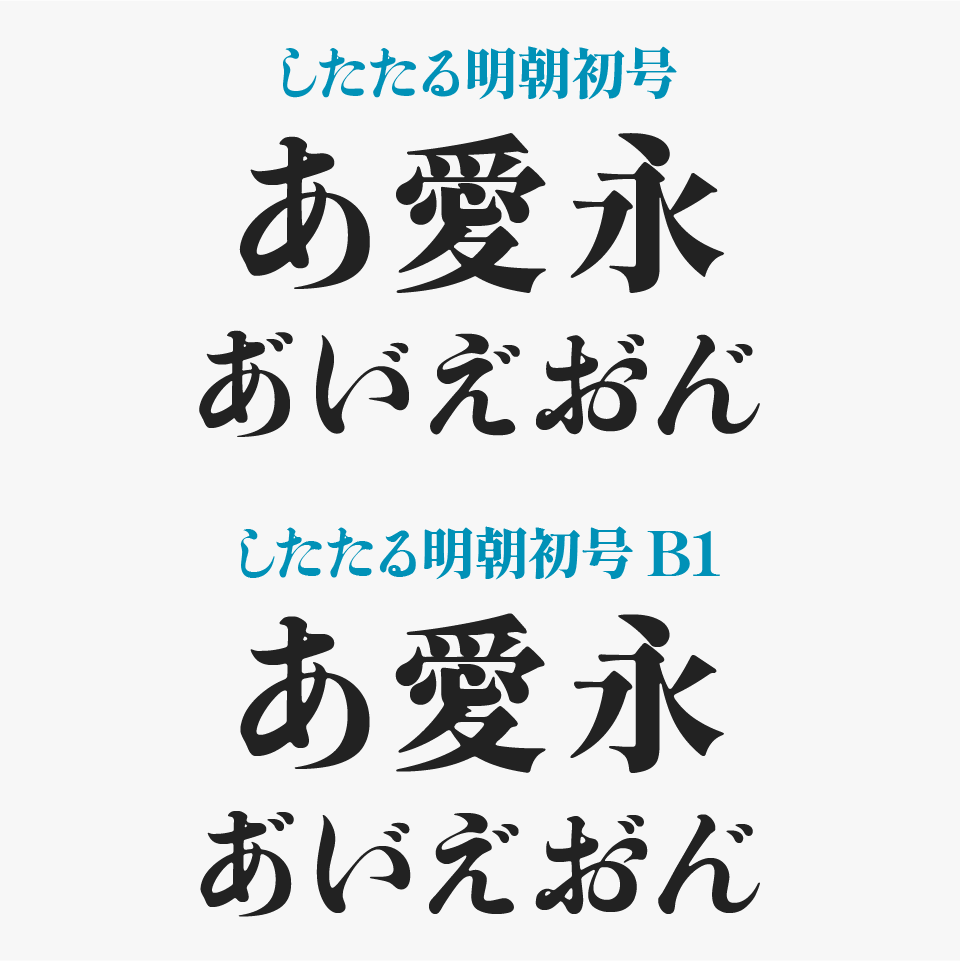
したたる明朝初号フォントは、築地系初号活字の重厚な骨格をベースに、墨がじんわりと滲み、したたり落ちるような湿度感をまとわせた日本語明朝フォントです。
仮名は筆の流れを活かして可能な限りつなげることで、活字らしい品格と筆文字の色気を両立。漢字には「源流明朝」をベースにエッジへ丸みを加えた字形を採用し、拡大しても美しく見えるよう丁寧に調整されています。
したたる明朝初号
さらに、写植印刷時代の「ボケ足(墨だまり)」を再現した別バージョン「したたる明朝初号B1」も用意されており、より深みのある表現が楽しめます。濁点喘ぎ(汗喘ぎ・汗濁喘ぎ・濁音喘ぎ)や濁点付きハートマークなど、遊び心ある文字も収録。
ロックやバイオレンス、ホラー、時代劇、エロスといった濃密な世界観はもちろん、印象的なタイトルや装丁、ゲーム、映画ポスターなど、強い言葉を際立たせたい場面にぴったりなフォントです。
したたる明朝初号としたたる明朝初号B1を比較